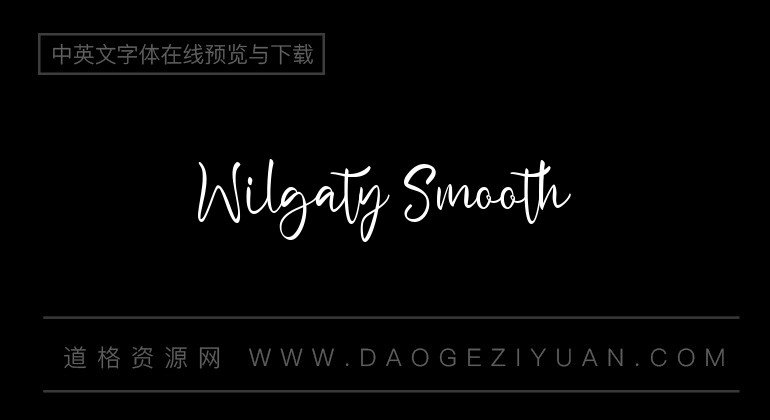
Wilgaty Smooth
? Wilgaty Smooth 字体是一款简洁、优雅的英文字体,具有极佳的可读性,适用于报纸、杂志、书籍、标识、广告等等。字体拥有宽松的节奏,具有温暖的感觉,可以带来温暖的气氛。字体的笔画细腻,给人以柔和的感觉,具有良好的可读性。
Wilgaty Smooth是一款非常不错的手写艺术字体,具有很好的视觉感,适合于文化类的宣传设计、商业类品牌的广告和产品包装设计以及个性化文字排版等较多场景。